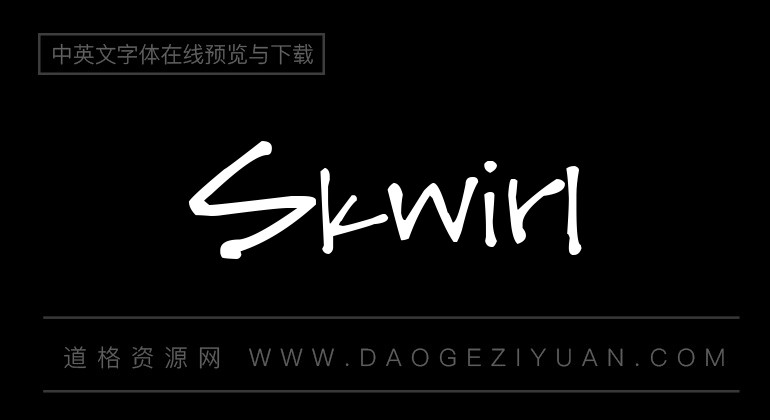
Skwirl
Skwirl 字体是一种拥有独特设计风格的字体,它充满动感,有趣,富有表现力。它由英国设计师Paula Nazal创作,带有柔和的曲线,更多的可爱感。它的字体粗细可以调整,有大量的细节,比如拉伸的线条,形状的变化等。Skwirl 字体可以用于各种印刷制品,如海报,书籍,画册等,也可以用于网页设计、平面设计等。
Skwirl是一款非常不错的手写艺术字体,具有很好的视觉感,适合于文化类的宣传设计、商业类品牌的广告和产品包装设计以及个性化文字排版等较多场景。